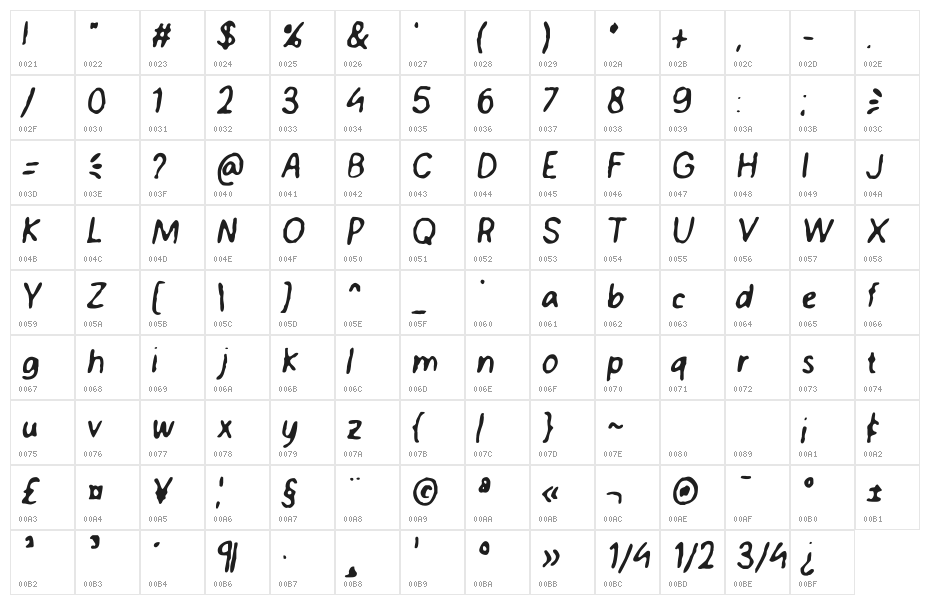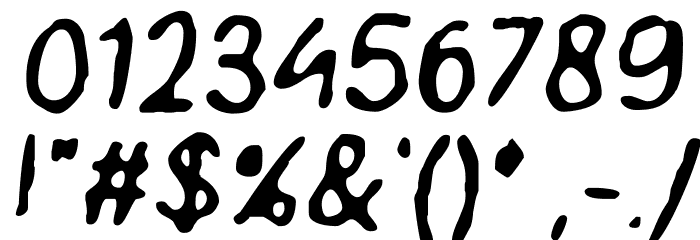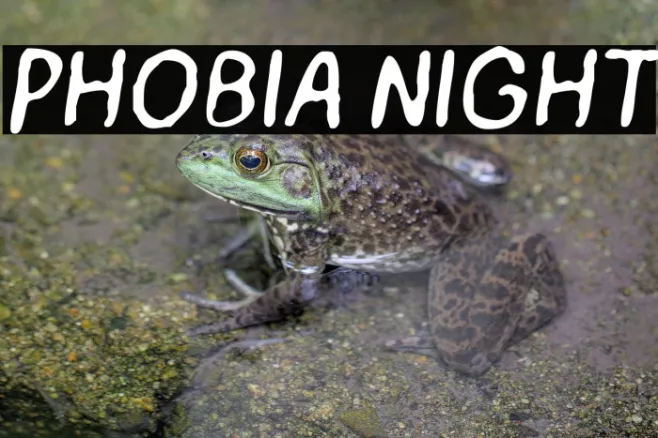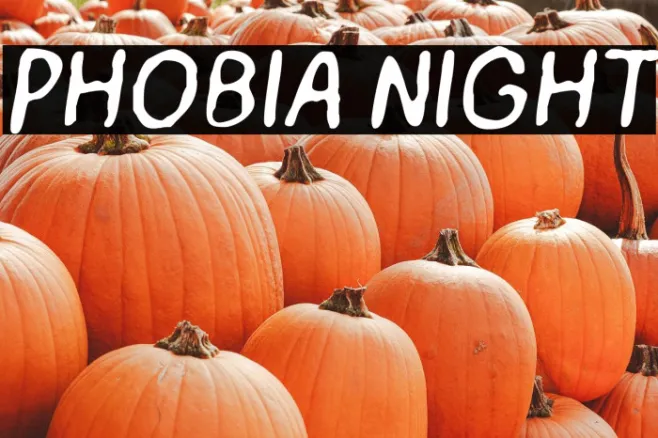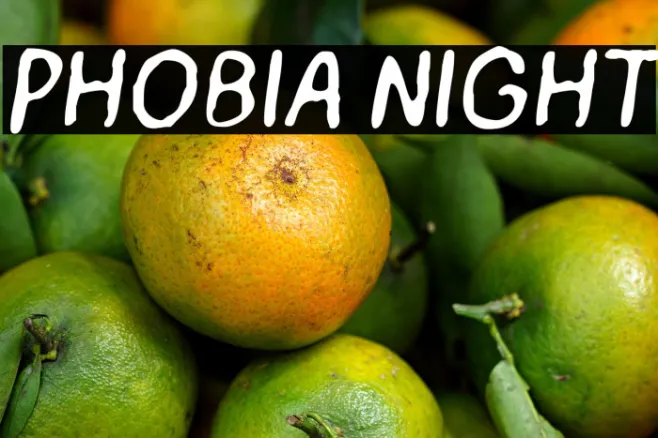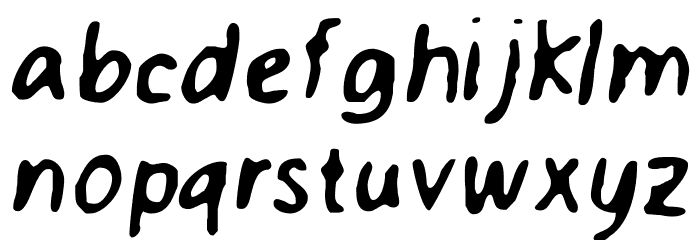
PHOBIA NIGHT Font
| Anwendungsfall | Logos, Posters, Invitations |
| Vorgeschlagene Projekte | Ideal for creative projects such as children's books, artistic posters, casual branding, and playful invitations. |